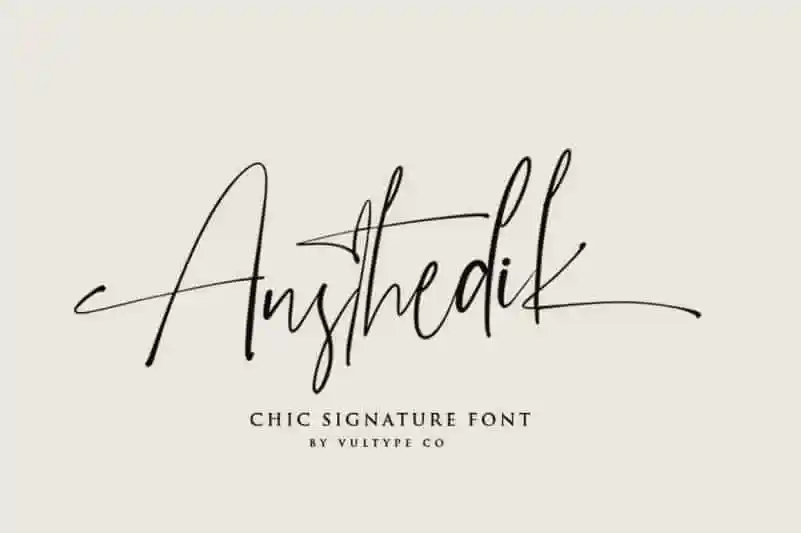
Austhedik Script Font – Download Grátis
A Austhedik Script Font é uma elegante coleção de letra cursiva que transporta você para ambientes cheios de frescor tropical durante as férias de verão. Desenvolvida pelo designer Vultype Co, esta fonte traz um toque delicado e fluído à sua tipografia, complementada por ligaturas e alternativas que adicionarão um toque atraente aos seus projetos. Perfeita para criar mensagens pessoais ou personalizar designs de forma sofisticada, a Austhedik Script Font é uma excelente opção se você busca algo além da rotina padrão, oferecendo sempre uma dose de natureza tropical e elegância na sua escrita digital. Combinar esta fonte com outros recursos gráficos leva ao desenvolvimento de projetos que não só são originais e imprimíveis, mas também proporcionam um conforto visual agradável e frescor alegre, característicos da estação do ano mais quente no Brasil.